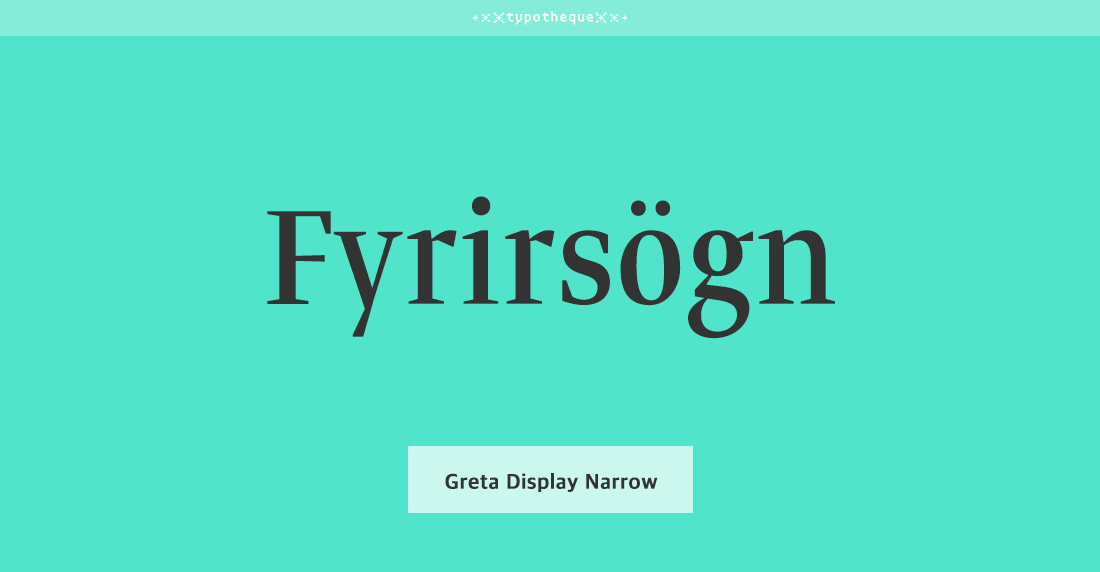
- Greta Display Narrow Std는 글자의 대조는 높이고 간격을 좁히고 세밀한 세부 정보를 제공하도록 설계되었다.
특히 디스플레이 글꼴은 우아하고 콤팩트하며 큰 크기로도 적합해 헤드라인 영역이나 인쇄물 등에 사용할 수 있다.
Narrow는 베이직한 Display 폰트보다 자폭이 더 좁아 좁은 공간에서 더 유용하게 사용이 가능하다.
폰트 정보 구분 명조 디자인디렉팅 Peter Biľak, Nikola Djurek 출시년도 2008